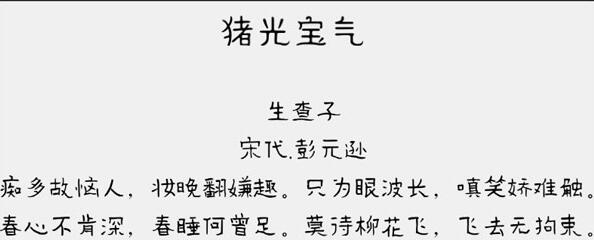
豬光寶氣字體是一款十分好用,且非常漂亮的中文字體,同時(shí)也是由文道字庫傾情發(fā)布,字體筆畫撇較粗,凸顯其獨(dú)特的行書魅力,整體效果非常賞心悅目,適合應(yīng)用于藝術(shù)設(shè)計(jì)、平面宣傳設(shè)計(jì)、網(wǎng)頁設(shè)計(jì),書法字帖等領(lǐng)域,也可以應(yīng)用于文本裝潢、信息展示、篆刻制模英文、數(shù)據(jù)制作、裝潢設(shè)計(jì)、視覺設(shè)計(jì)、字帖等一切合法應(yīng)用場(chǎng)景,有喜歡的朋友可免費(fèi)下載收藏。